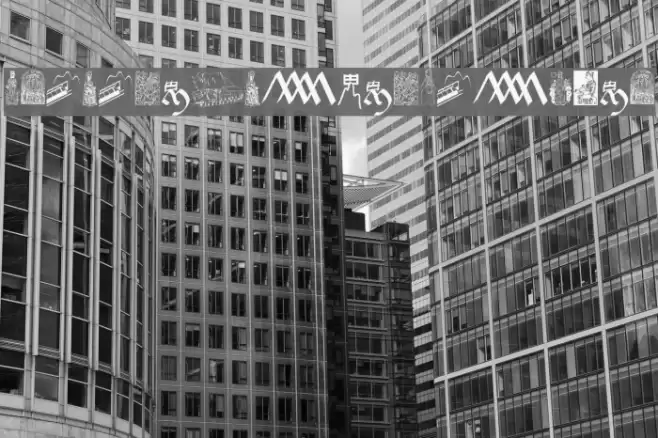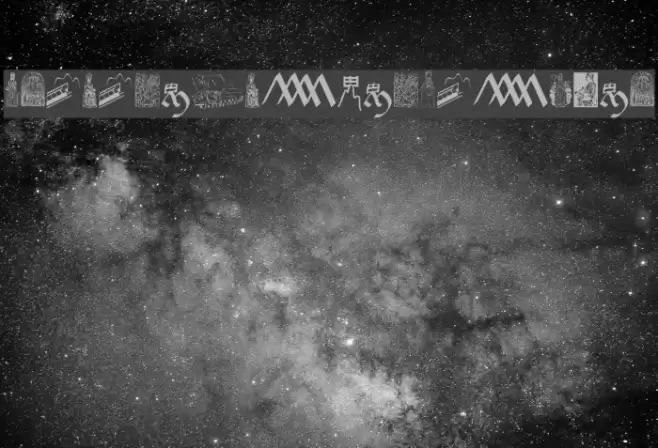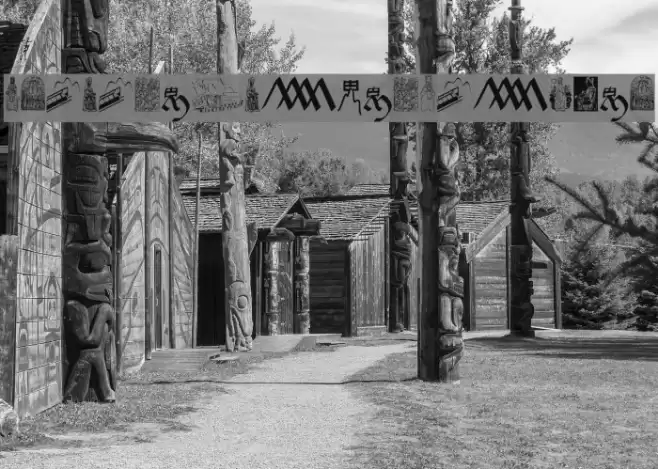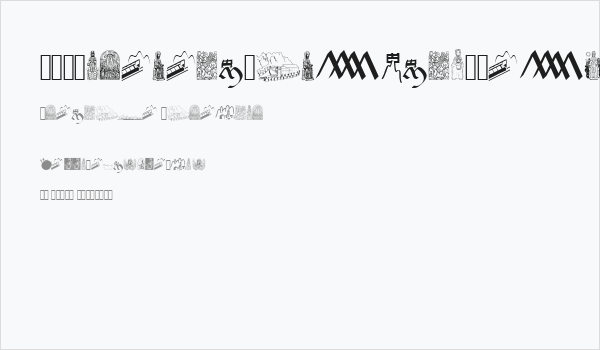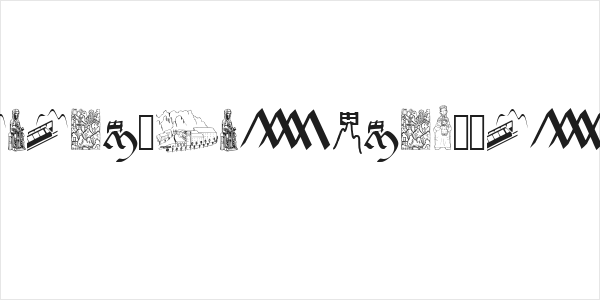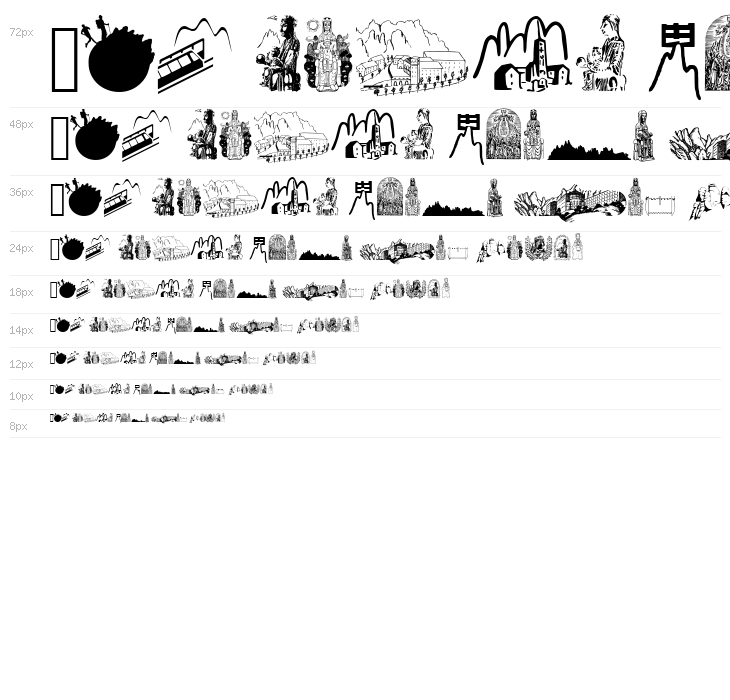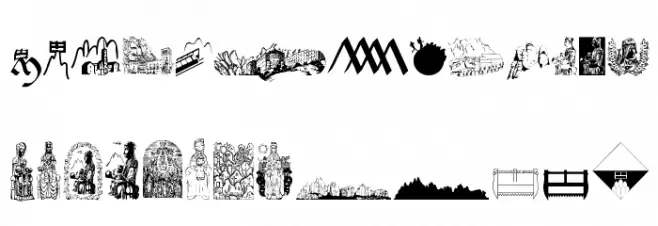
JMHMorenetaDingbats-Regular Font
| कंट्रास्ट | High |
| समग्र शैली | Decorative |
| उपयोग का मामला | Logos, Decorative elements, Themed designs |
| सुझाए गए प्रोजेक्ट | Ideal for cultural event posters, artistic projects, themed invitations, and decorative elements in graphic design. |